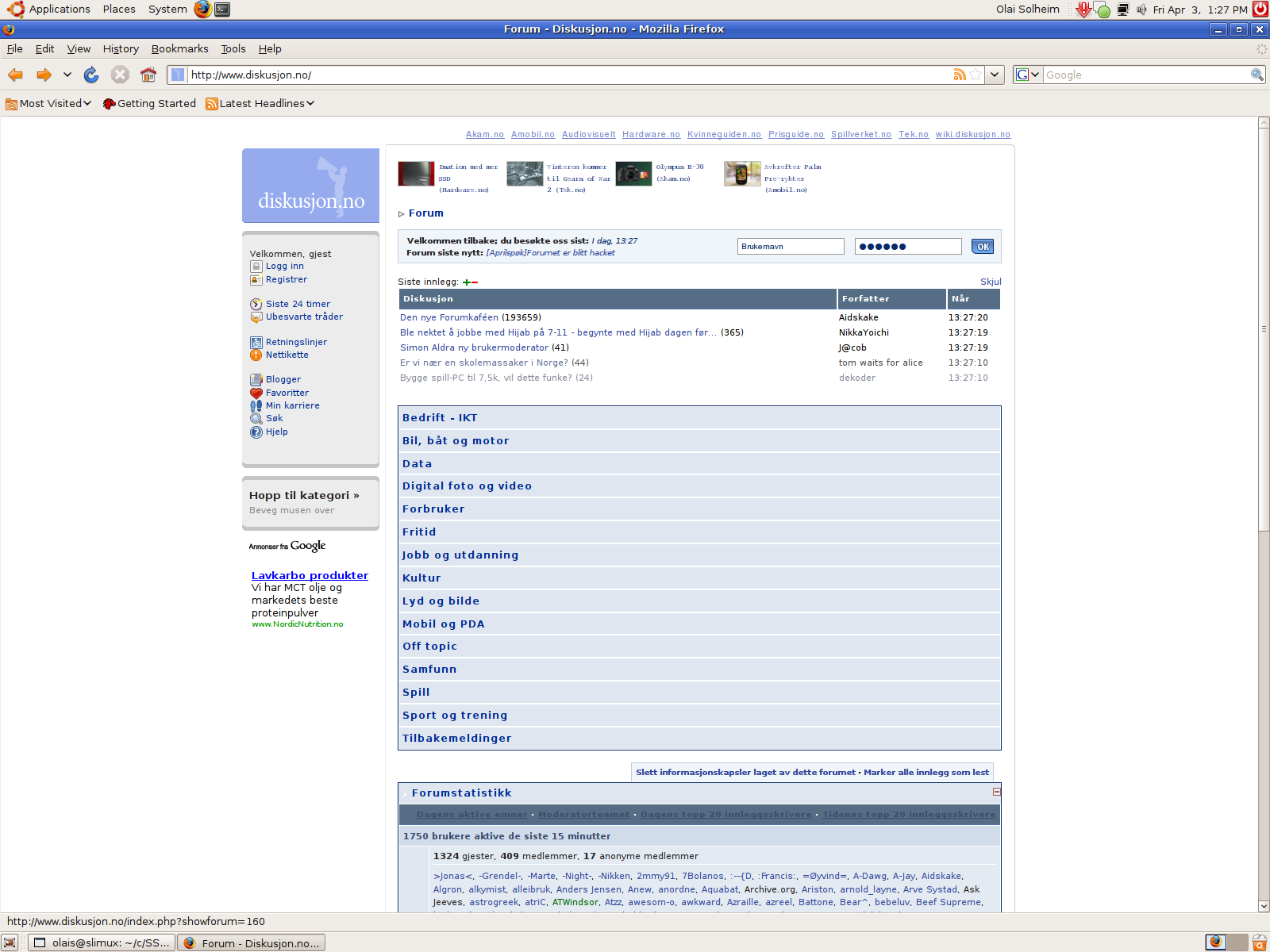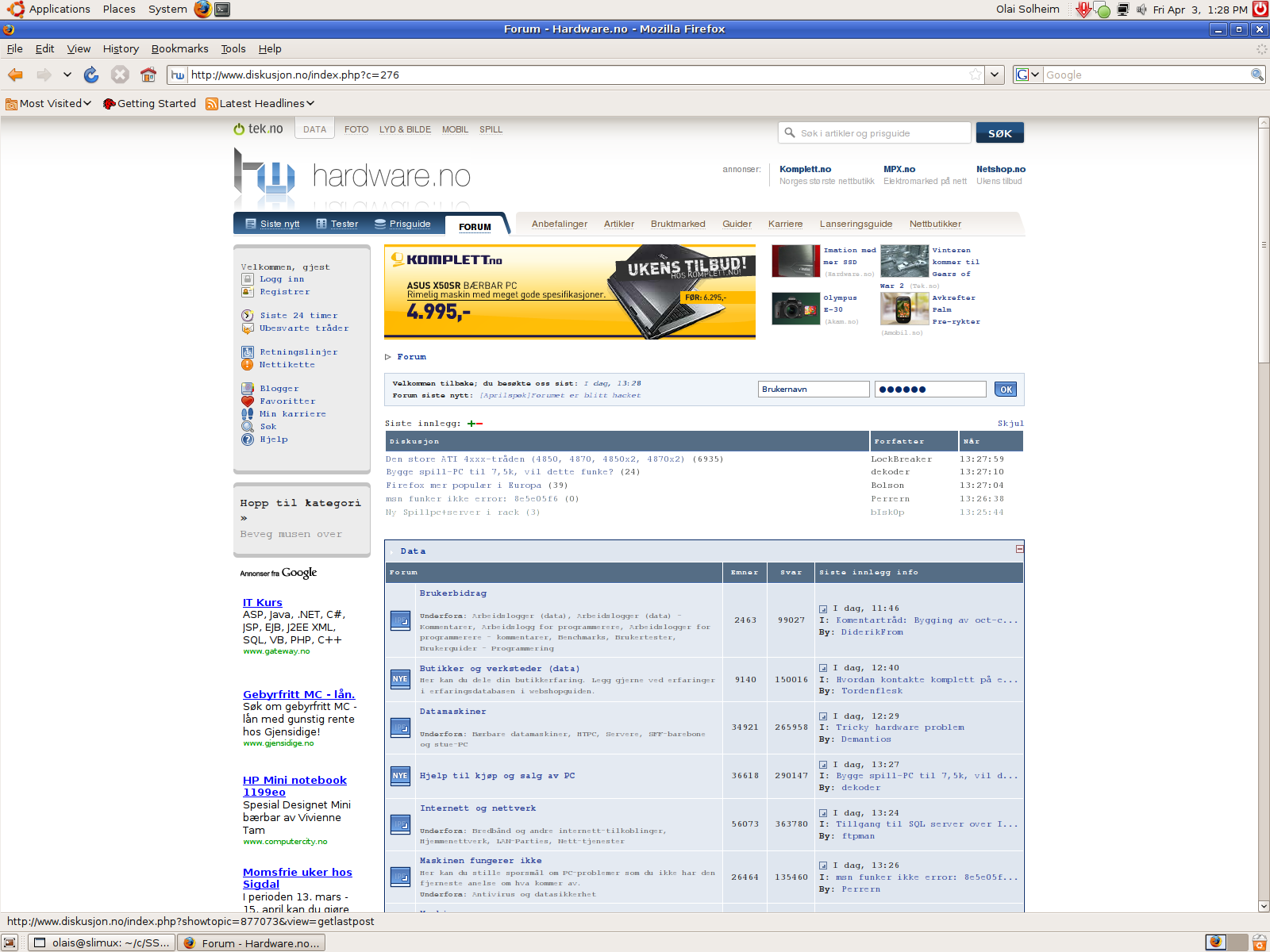
LostOblivion Skrevet 3. april 2009 Hei, Sitter på en Ubuntu Linux 8.02 med Firefox 3.0.7 og når jeg besøker Hardware.no-delen av forumet, prøver nettleseren å vise en monotype-font i stedet for sans-serif fonten som er vanlig i de andre delene av forumet. Denne svært lille monotype-fonten er svært irriterende. La ved noen bilder.